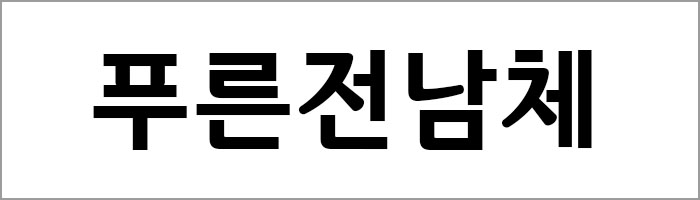
지역폰트가 있는 여름휴가지 추천 3곳
올해 여름은 매일 기록 경신 중이다. 아침 뉴스를 보니, 지난밤 서울의 최저 기온은 30.4도로 111년 만에 가장 높았다고 한다. 어쩐지 잠을 자도 개운하지가 않고 기운이 없다. 지하철에서 마주치는 사람들은 모두 어깨가 축 처진 안쓰러운 모습이다. 이럴 때 필요한 것이 바로 꿀 같은 휴가가 아닐까? 무료 폰트를 제공하고 있는 지역 중에서 여름휴가 떠나기 좋은 곳을 모아봤다. 그 지역에서 정말 폰트가 잘 쓰이고 있는지 찾아보는 것도 새로운 재미일 것이다.
1. 제주 사려니숲
제주는 바다 못지않게 초록색 아름다움이 넘치는 섬이다. 아직 개발되지 않은 조천읍 교래리에는 신성한 숲이라는 뜻을 지닌 ‘사려니 숲’이 있다. 비자림로에서 출발하여 붉은 오름 입구까지 총 15km의 트레킹 코스로, 편도로 다 걸으려면 3시간 정도가 소요된다. 꽤 긴 시간이지만 주로 평지인 데다가 화산송이 흙길이어서 걷는 것을 좋아한다면 완주할 것을 추천한다. 쭉쭉 뻗은 삼나무 사이로 걷다 보면 잡념이 사라지고, 피톤치드를 만끽할 수 있을 것이다. 또한 성수기에도 사람들이 많지 않아 자연에서 조용히 쉬고 싶은 사람에게 안성맞춤이다.
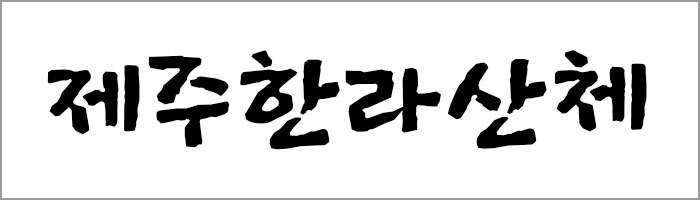
제주 한라산체
화산섬인 제주의 이미지에서 떠오르는 구멍이 뚫린 현무암과 같은 지질학적인 요소를 투박하면서도 부드럽게 담아낸 폰트이다. 산돌커뮤니케이션에서 제작했다. 영상, 인쇄, 웹, 모바일 등 다양한 매체에 자유롭게 사용할 수 있으며, 특별한 허가절차 없이 사용 가능하다.
2. 부산 송도 해수욕장
여름에는 바닷속으로 풍덩 빠져야 하는 사람들이라면 부산의 송도해수욕장으로 떠나보는 것은 어떨까? 1913년, 부산에서 처음으로 개장한 ‘송도 해수욕장’은 해운대, 광안리보다는 비교적 덜 붐벼 친구, 가족과 오붓한 물놀이가 가능하다. 또한 거북이 모양의 다이빙대가 있어서 색다른 바다 다이빙을 즐길 수 있다. 밤이면 구름다리에 올라서서 야경을 감상할 수 있고, 작년에 개장한 송도해상케이블카를 타며 부산의 바다를 하늘에서 내려다볼 수 있다. 볼거리, 즐길 거리, 먹을거리를 모두 누리고 싶은 사람에게 추천한다.
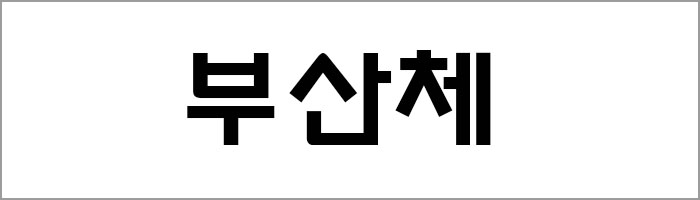
부산체
2010년에 보급되어 전체적으로 모던함과 세련미를 드러낸 폰트이다. 부산시는 앞으로 고유글꼴을 지속해서 추가 개발하여 디자인 도시로 거듭나고자 한다. 부산체는 누구나 무료로 내려받아 자유롭게 사용할 수 있다.
3. 담양 죽녹원
여름밤 시골에서 볼 수 있던 ‘죽부인’의 고장, 담양은 대나무로 유명한 지역이다. 죽녹원은 담양을 대표하는 대나무숲으로, 외부보다 4도에서 7도 정도 온도가 낮아 여름에도 시원하다. 총 2.4km의 아담한 산책로는 길에 이름이 붙여져 있어 걷는 재미가 있다. 또한 죽녹원 안에 있는 한옥에서는 숙박을 할 수 있다. 느린 휴가를 즐기고 싶다면 대나무 숲에서 하루 묵으며 풍류시인이 되어보는 것은 어떨까. 후문 청죽헌 옆 카페 추월당에서 사색에 잠기는 것도 추천한다.
푸른전남체
다도해의 출렁이는 바닷물결을 모티브로 한 폰트이다. 젊고 푸른 느낌을 담아내려 했으며 속공간을 고려하여 가독성을 높이려 했다. 윤디자인에서 제작했으며, 푸른전남체는 특별한 허가 절차 없이 사용할 수 있으나 상업적 행위와 재배포는 금지되어 있다.